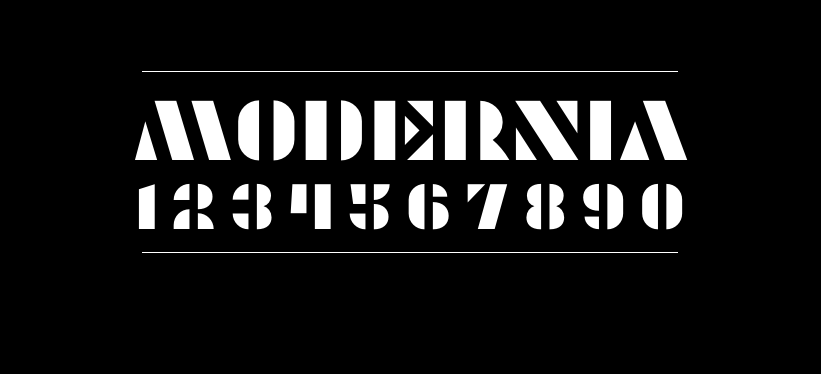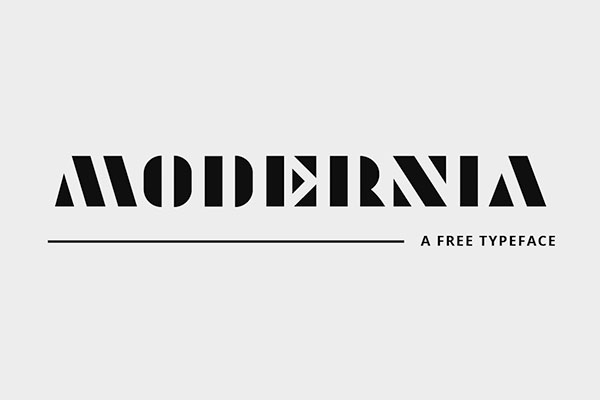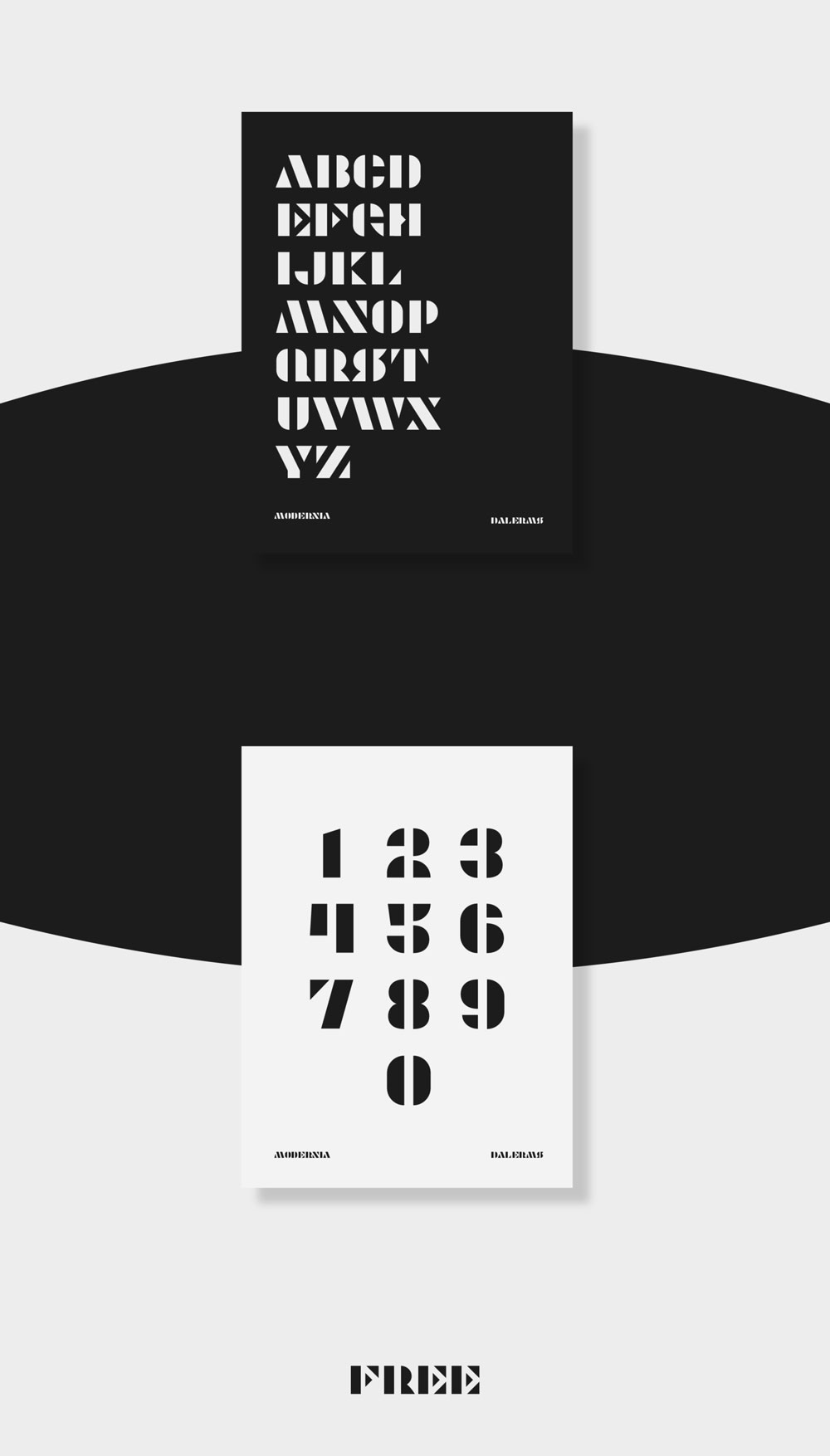
Modernia是来自美国的设计师Daler Mukhiddinov创作的英文字体,该字体采用简约造型,删减了字母中的部分笔画,同时将剩余笔画加强加粗,极具设计感。可用于海报、标题、印刷等场合。该字体首发于Behance,遵循Open Font License (OFL)开放字体协议,个人及商用免费。